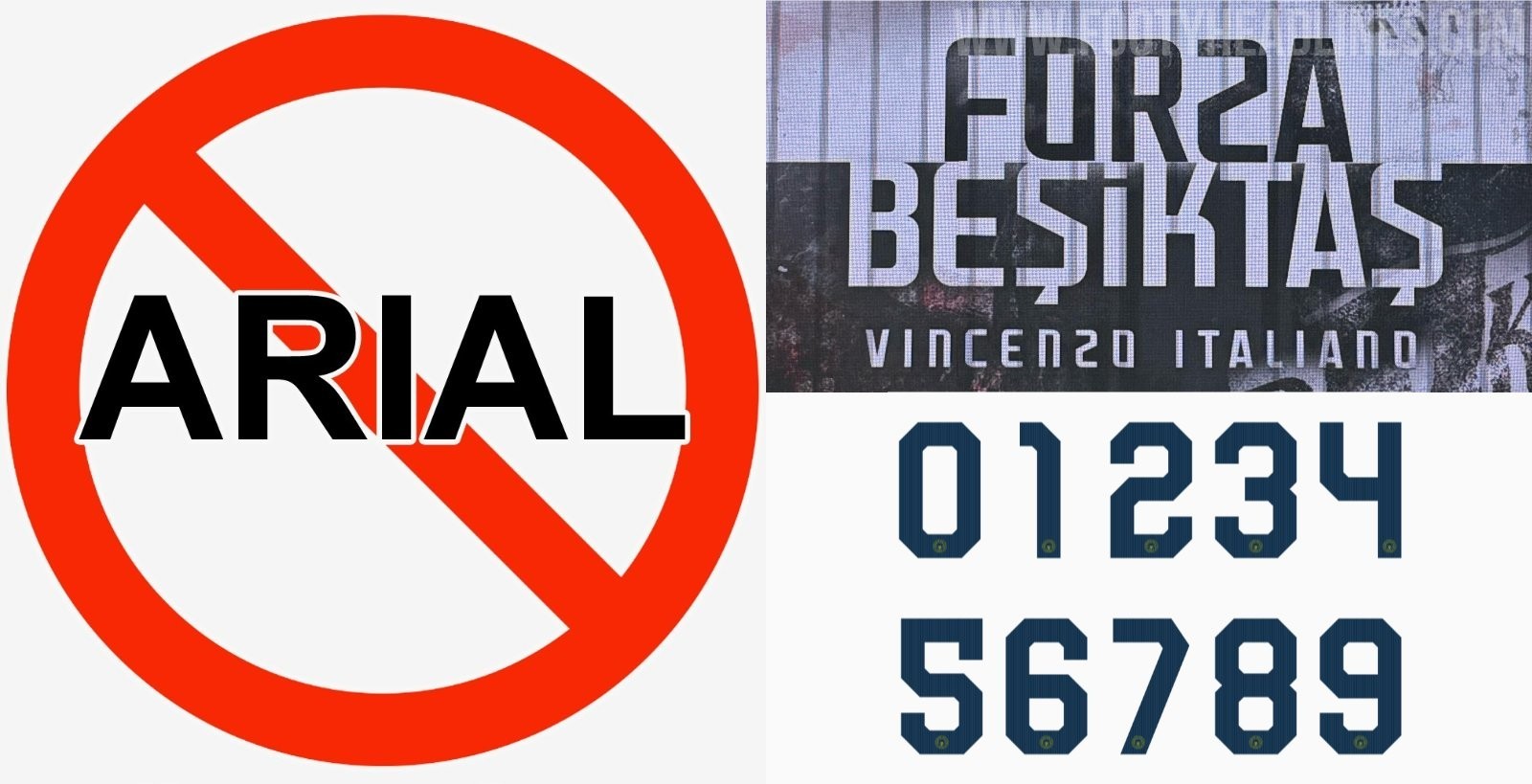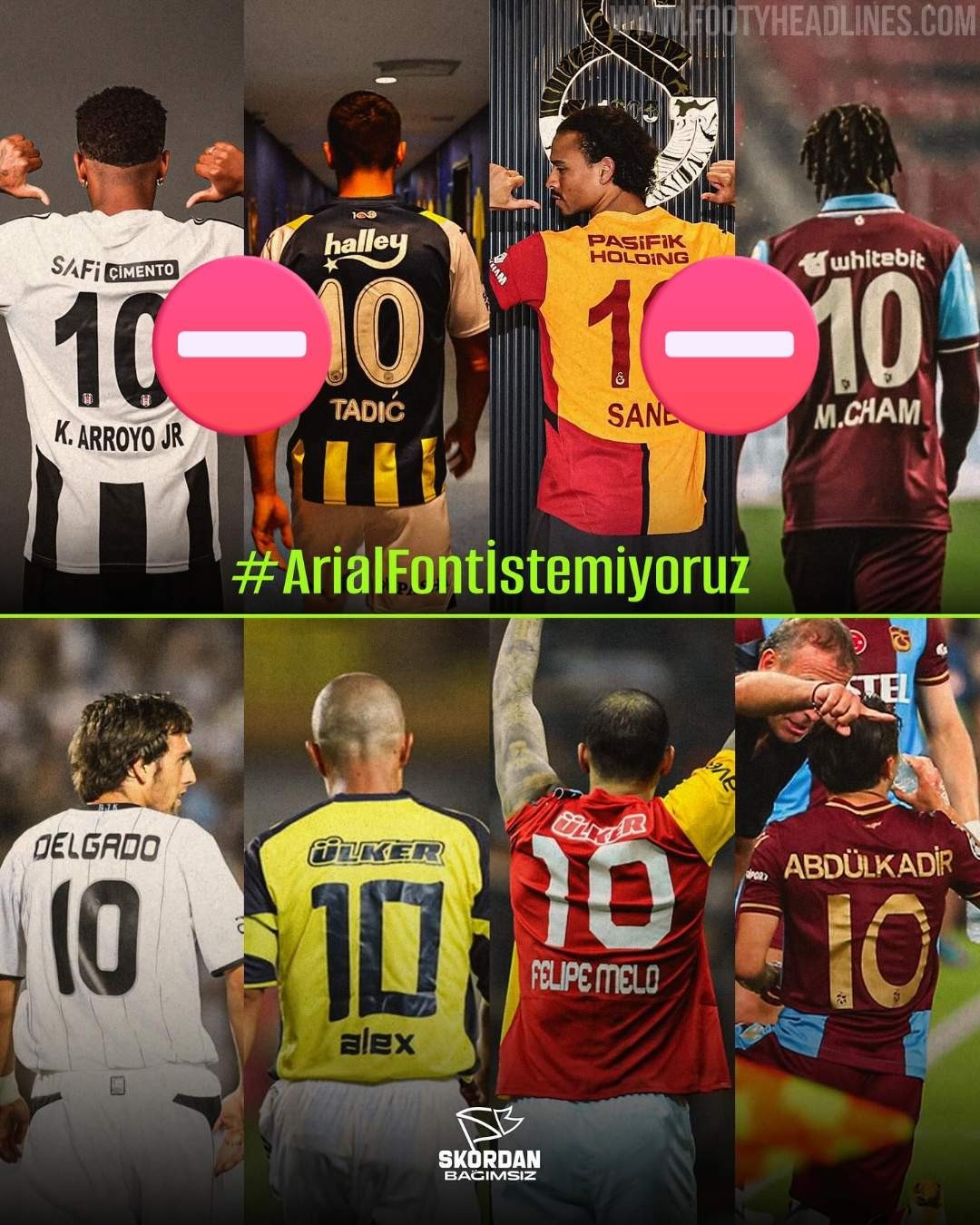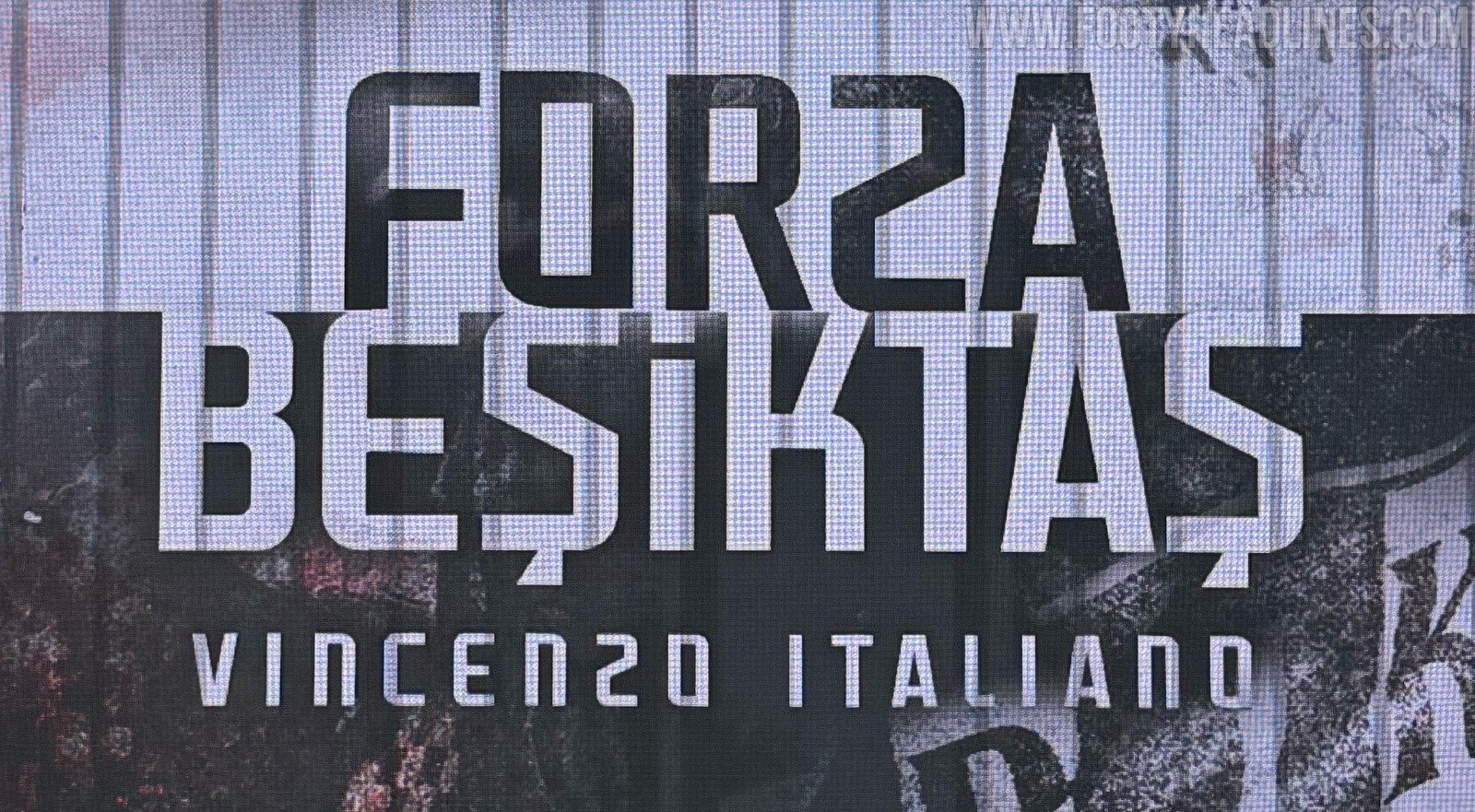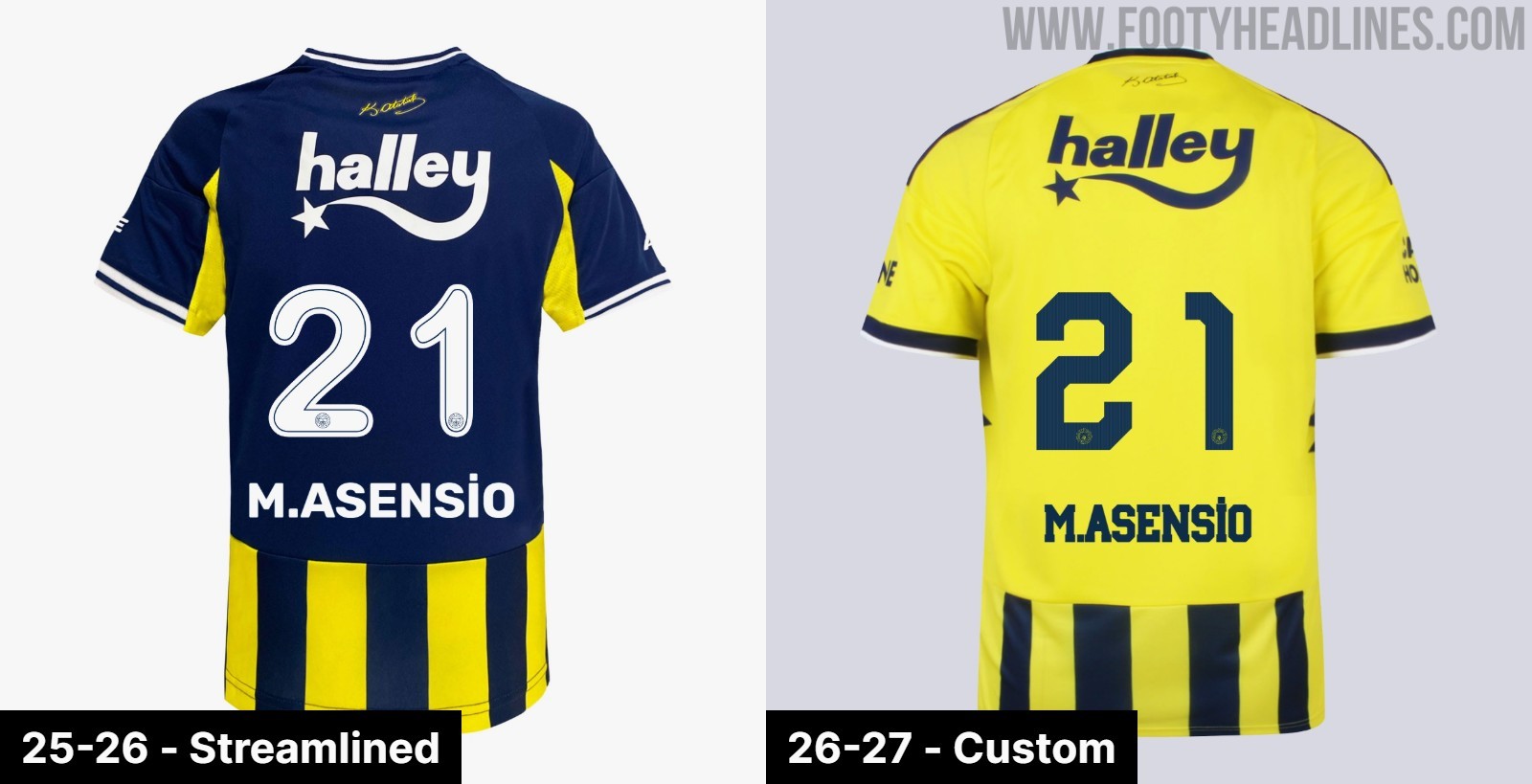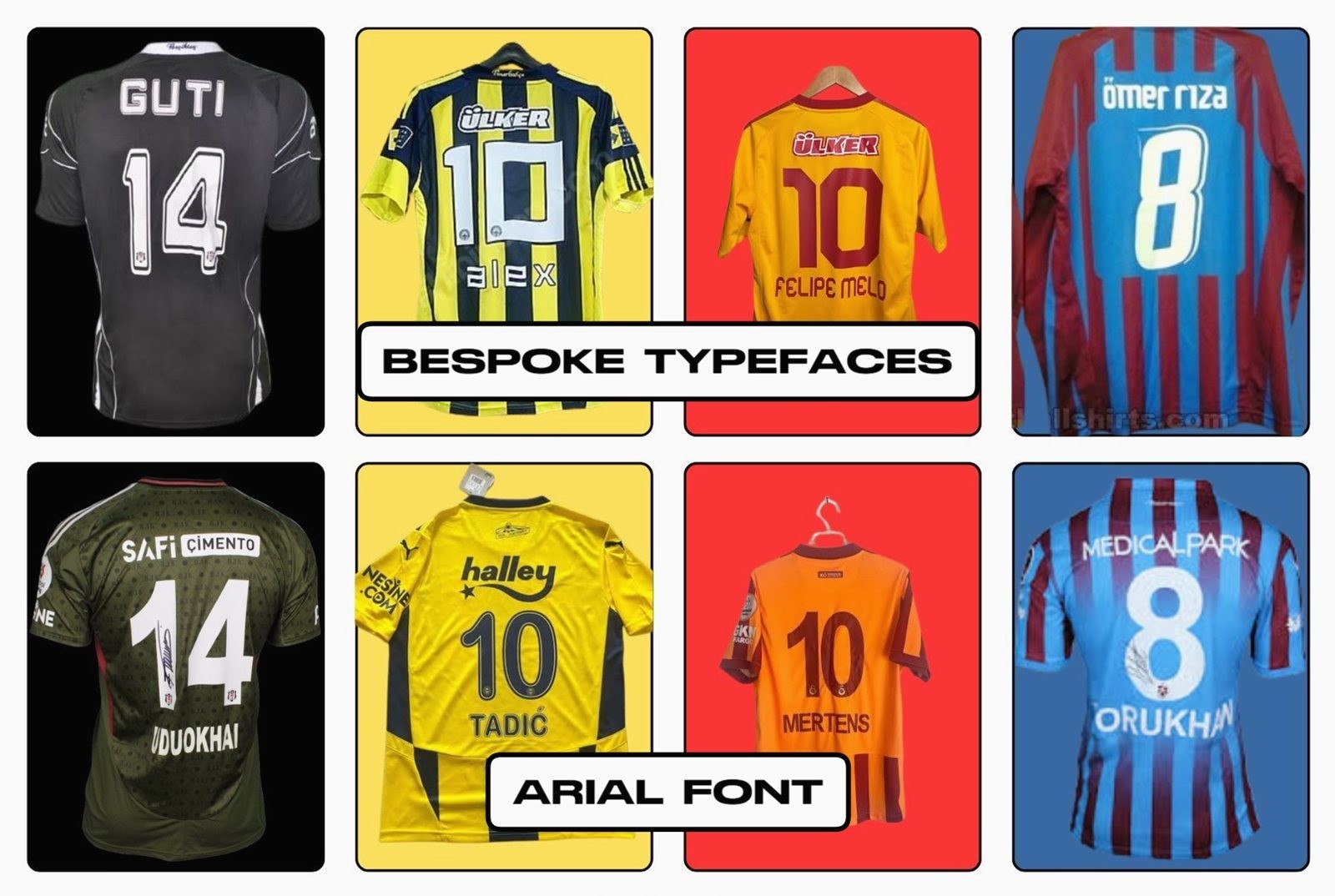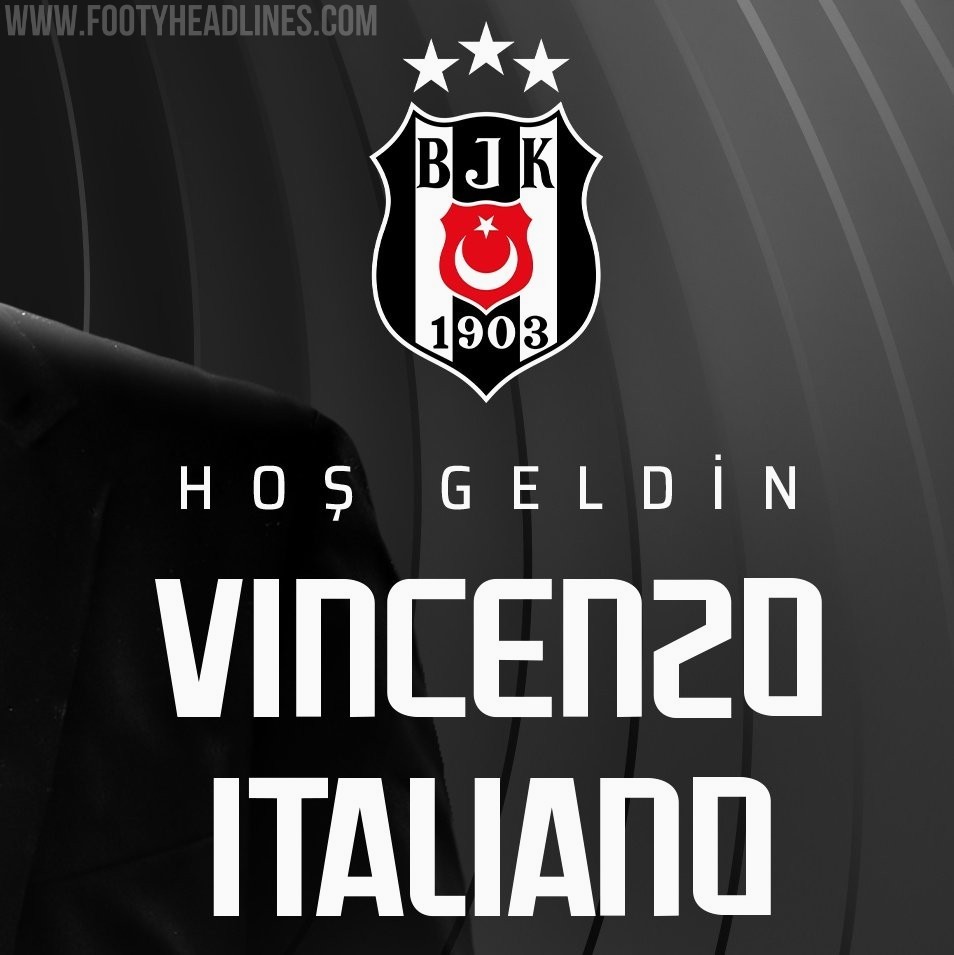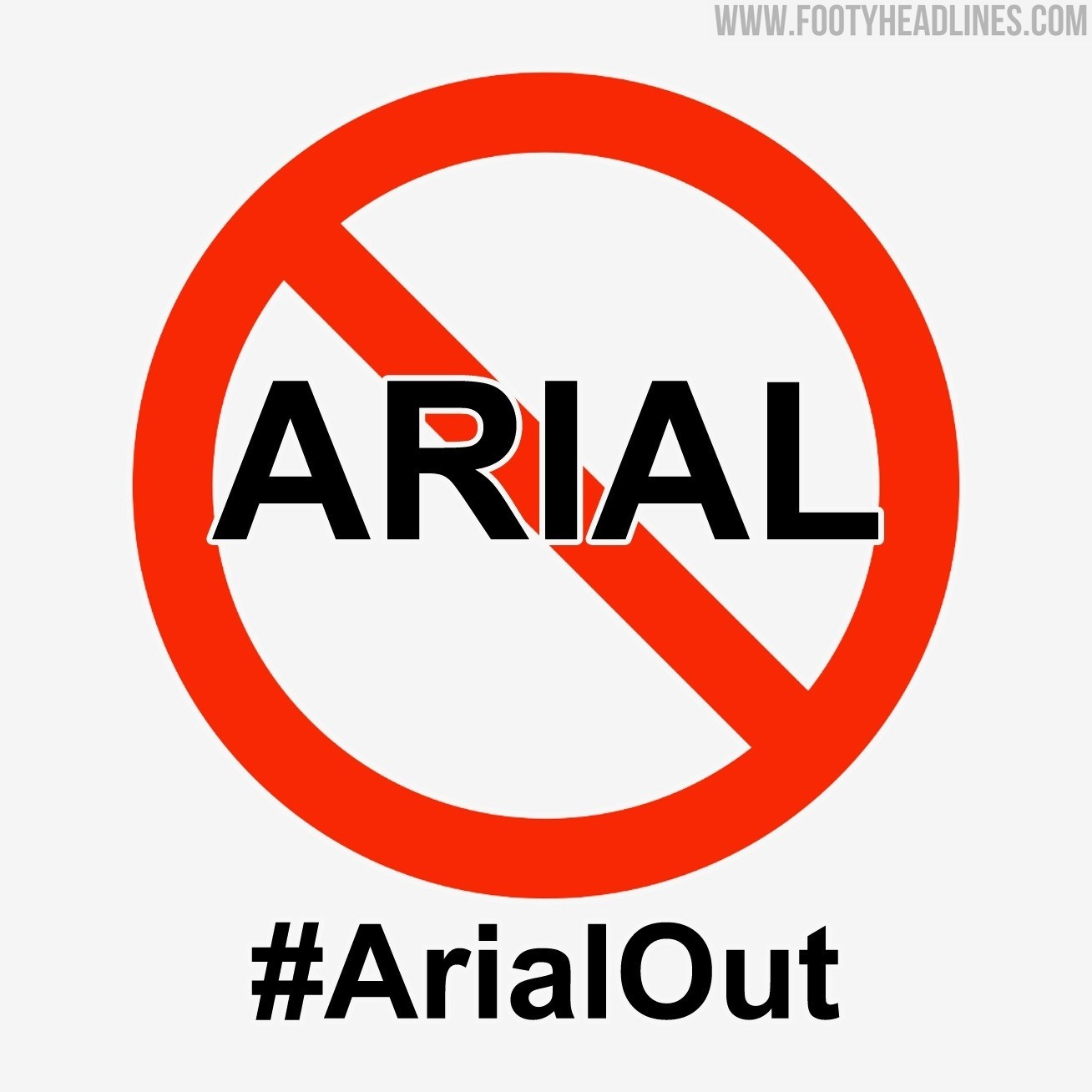
Ende der Arial-Ära in der Süper Lig: Vereine haben für die Saison 26/27 eigene Schriftarten für ihre Trikots
• Ende der Arial-Ära: Nach jahrelangen Fanprotesten hat der türkische Fußballverband (TFF) die obligatorische Verwendung der standardisierten Arial-Schriftart für Trikots in der Süper Lig offiziell abgeschafft.
• Umsetzung ab Saison 2026/27: Obwohl die Entscheidung im Juli 2025 getroffen wurde, können die Vereine die neuen individuellen Schriftarten aufgrund der Produktionszyklen erst vollständig in der Saison 2026/27 auf ihren Trikots umsetzen.
• Individuelle Schriftarten für Top-Clubs: Große Vereine wie Fenerbahçe, Beşiktaş und Galatasaray werden die neu gewonnene kreative Freiheit nutzen, um für die Saison 2026/27 eigene, maßgeschneiderte Schriftarten für ihre Trikots einzuführen.
Seit über einem Jahrzehnt äußern türkische Fußballfans ihre Frustration über ein scheinbar unbedeutendes, aber dennoch äußerst wirkungsvolles Detail an den Trikots ihrer Mannschaften: die Schriftart. Seit 2012 schrieb der türkische Fußballverband (TFF) allen Vereinen der Süper Lig streng vor, für Spielernamen und Rückennummern eine standardisierte, generische Arial-Schriftart zu verwenden. Während andere große europäische Ligen ihre visuelle Identität kontinuierlich mit modernen, maßgeschneiderten Schriftarten aktualisierten, blieb die Süper Lig in einer visuellen Sackgasse stecken. Doch nach Jahren intensiver Fanproteste und Social-Media-Kampagnen unter Hashtags wie #ArialOut ist die „Arial-Ära“ nun offiziell vorbei.
Ende der Arial-Ära in der Süper Lig: Vereine haben für die Saison 26/27 eigene Schriftarten für ihre Trikots
Der TFF hat die obligatorische Verwendung der Standardschriftart im Juli 2025 offiziell abgeschafft und den Vereinen damit die kreative Freiheit gegeben, ihre eigene Typografie zu wählen. Zwar kam die Entscheidung zu spät, als dass die Vereine die Änderungen noch für die Saison 2025/26 umsetzen konnten – da die Trikotdesigns und Produktionsläufe bereits Monate zuvor festgelegt worden waren –, doch die Auswirkungen dieser wegweisenden Entscheidung werden in der kommenden Saison 2026/27 voll zum Tragen kommen.
Was dich 2026/27 erwartet
Während sich die Teams auf die Saison 2026/27 vorbereiten, die Mitte August beginnt, wächst die Spannung, wie die Vereine diese neu gewonnene kreative Freiheit nutzen werden.
• Fenerbahçe: Der Istanbuler Spitzenklub gehörte zu den ersten, die sich mit der Regeländerung befassten. Nach der Ankündigung der TFF im letzten Jahr veröffentlichte Fenerbahçe eine Erklärung, in der sie das Feedback der Fans würdigten und ausdrücklich erklärten, dass sie „dieses Feedback auswerten, um es in unseren Trikots für die nächste Saison umzusetzen“. Der Verein hat eine eigens entworfene Schriftart für seine Adidas-Trikots der Saison 2026–2027
• Beşiktaş: Die „Black Eagles“ starten in vielerlei Hinsicht in eine neue Ära. Sie werden nicht nur eine neue Schriftart einführen, sondern die Saison 2026/27 markiert auch den Beginn ihrer neuen Trikotpartnerschaft mit Nike, nachdem sie sich von Adidas getrennt haben.
• Galatasaray: Auch wenn konkrete Details zu Galatasarays Schriftwahl noch nicht offiziell bekannt gegeben wurden, wird der amtierende Meister diese Gelegenheit sicher nutzen, um seine Trikots mit einem maßgeschneiderten Design auszustatten, das seine ikonische Marke widerspiegelt.
Die Abschaffung der Schriftart Arial ist ein großer Sieg für die türkische Fußballkultur. Die generische Arial-Schriftart wurde von den Fans vielfach kritisiert und wirkte im Vergleich zu den maßgeschneiderten Schriftarten der Premier League, La Liga oder Serie A ausgesprochen uninspiriert. Jetzt haben die Vereine sogar noch mehr Grund zur Freude: Sie verfügen über eine eigene Schriftart.